## 概念
### 西文字体解剖
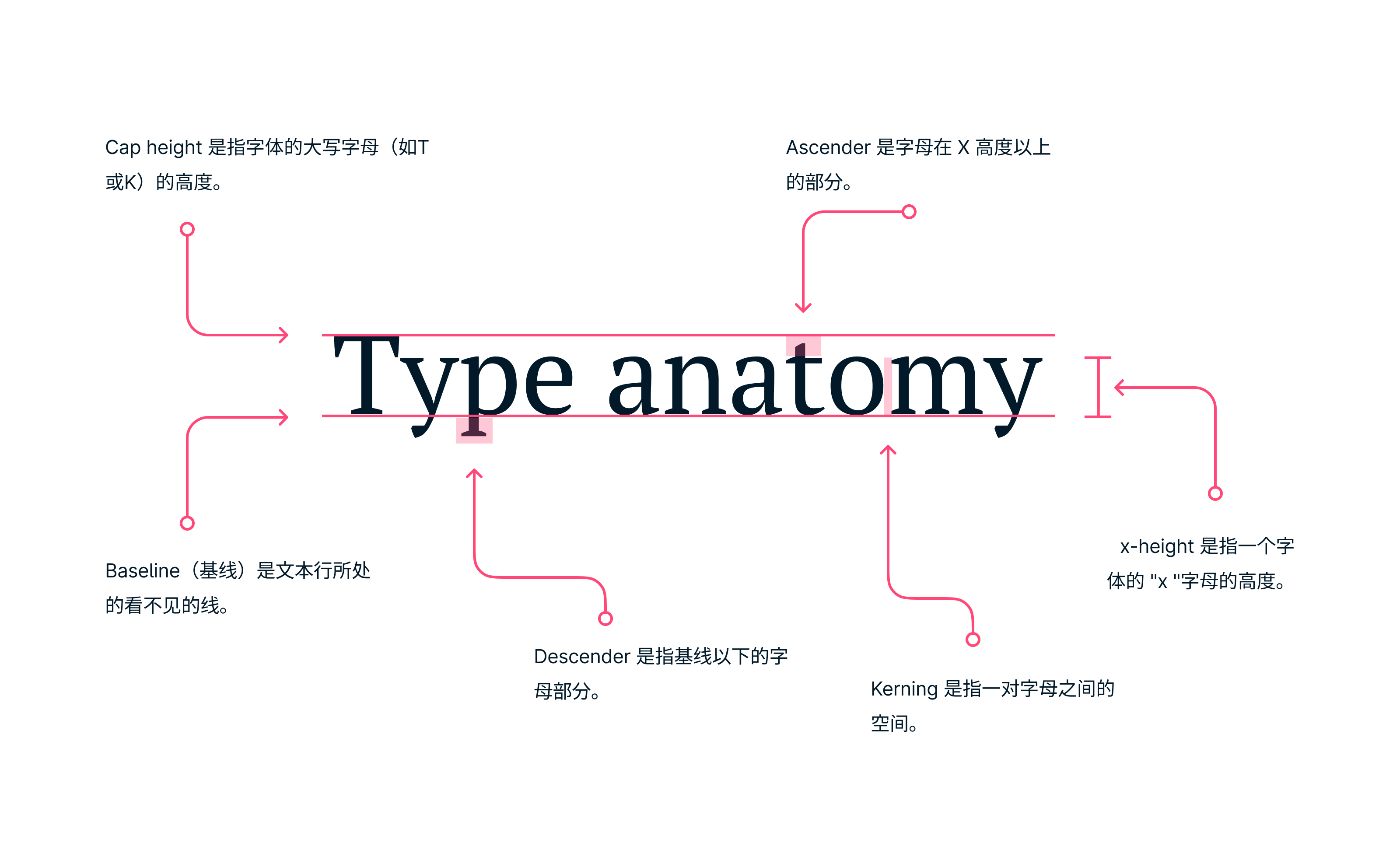
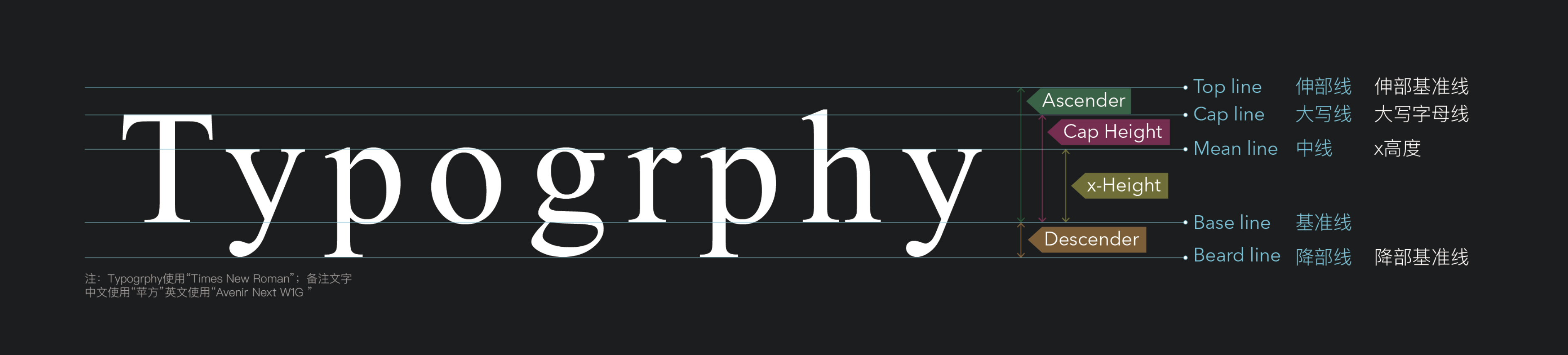
### 西文衬线体 Serif
#### Old Style 老式衬线体
老式衬线字体类似于用墨水书写。它们的特点是笔画粗细对比度低,笔画中存在对角线压力(见红线)。它们被认为是最传统的衬线风格。
老式衬线字体代表着历史和遗产。顾名思义,它们很古老。这就是说,它们中的许多--例如 Garamond--被认为是永恒的。如果你为一个具有悠久历史和传统的公司做设计,它们将是一个完美的选择,但对于专注于创新、进步和当前时代的公司来说,就不是一个好的选择了。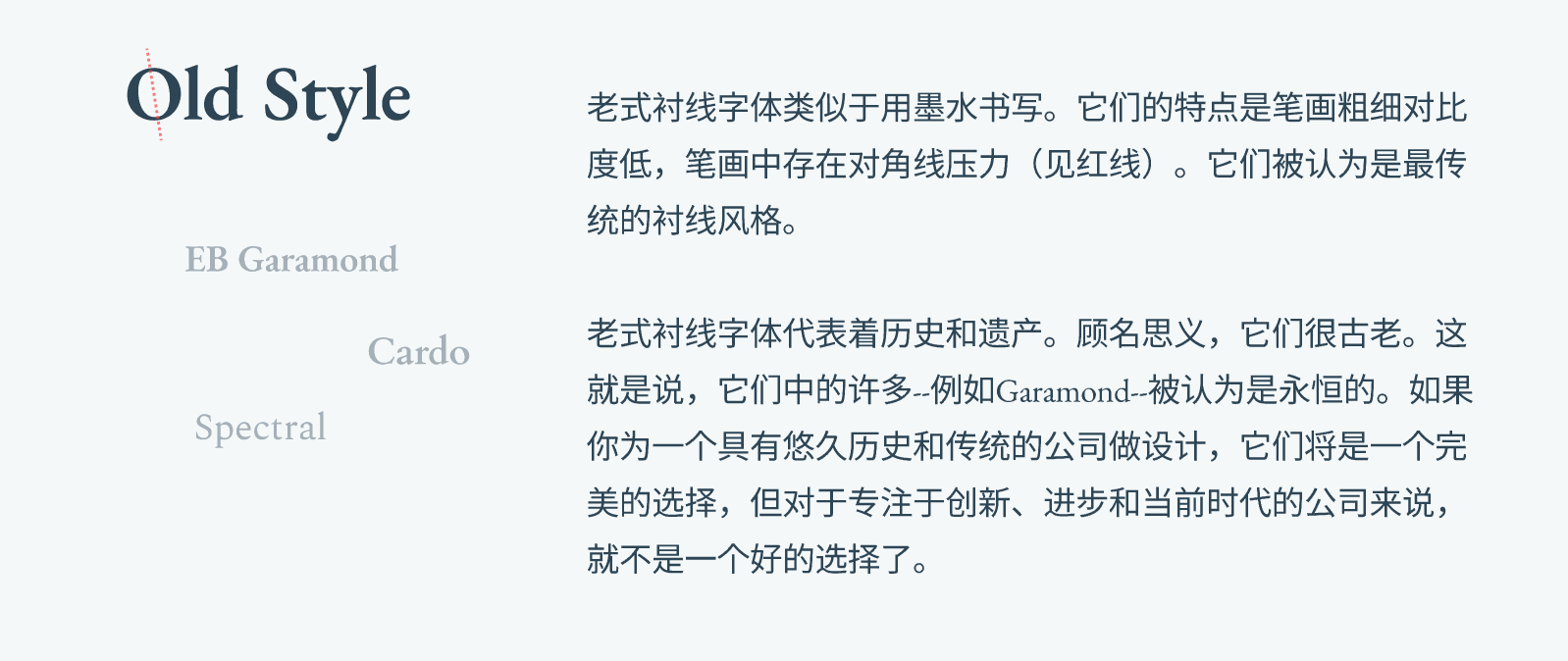
#### Transitional 过渡衬线体
过渡风格的特点是笔画的粗细对比度较高,笔画中的垂直压力较大(见红线)。与旧式风格不同的是,衬线也是有括号的。
过渡性衬线字体是非常通用的。它们是旧式风格和现代衬线之间的中间地带。这一类别的字体对于长篇文字来说是非常好的,例如用于**文章、博客文章甚至是书籍**。它们也代表着**安全、信任和传统**。
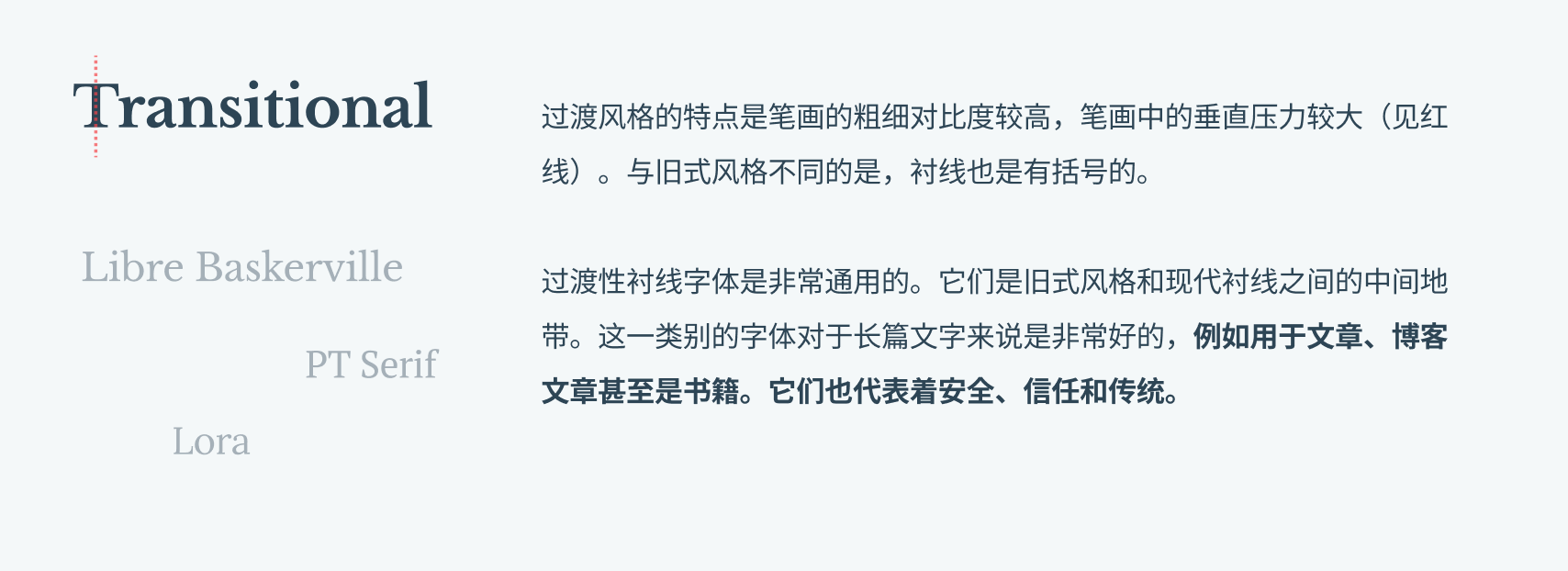
#### Neoclassical 新古典衬线字体
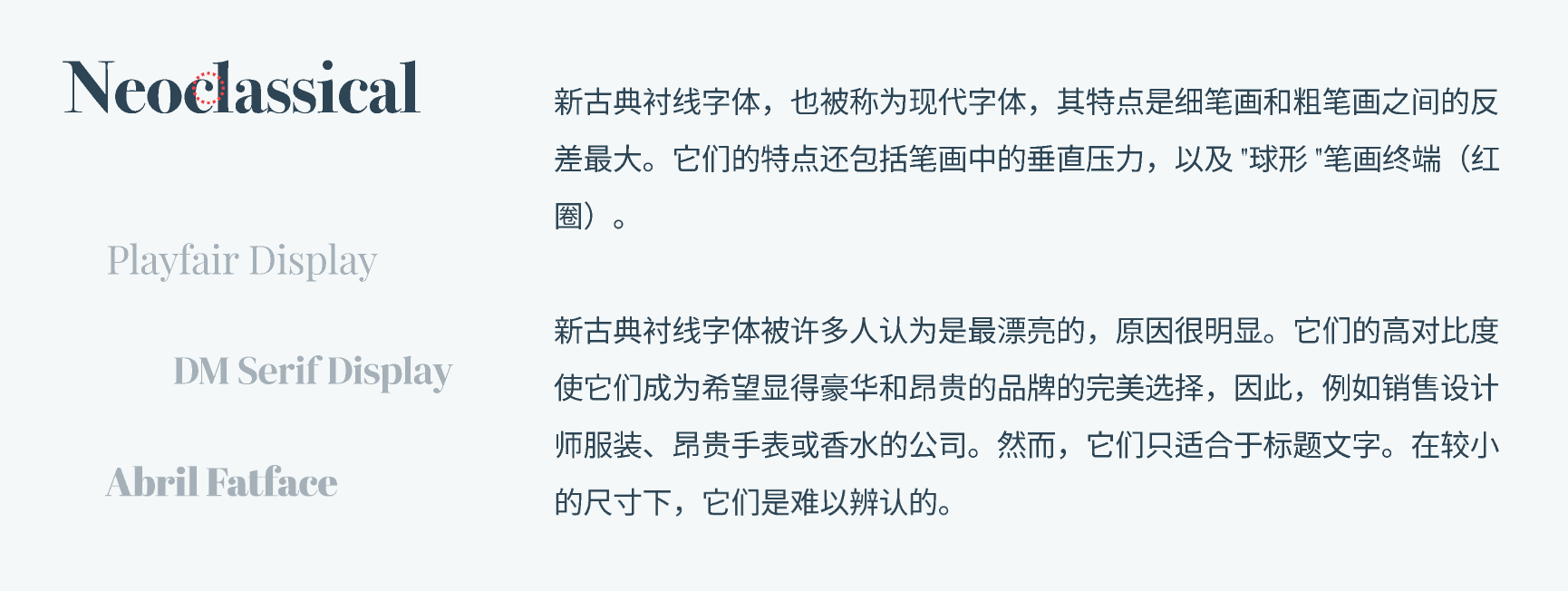新古典衬线字体,也被称为现代字体,其特点是细笔画和粗笔画之间的反差最大。它们的特点**还包括笔画中的垂直压力,以及 "球形 "笔画终端(红圈)。**
新古典衬线字体被许多人认为是**最漂亮**的,原因很明显。它们的高对比度使它们成为希望显得豪华和昂贵的品牌的完美选择,因此,例如**销售设计师服装、昂贵手表或香水**的公司。然而,它们**只适合于标题文字。在较小的尺寸下,它们是难以辨认的。**
#### Slab Serif 板式衬线体
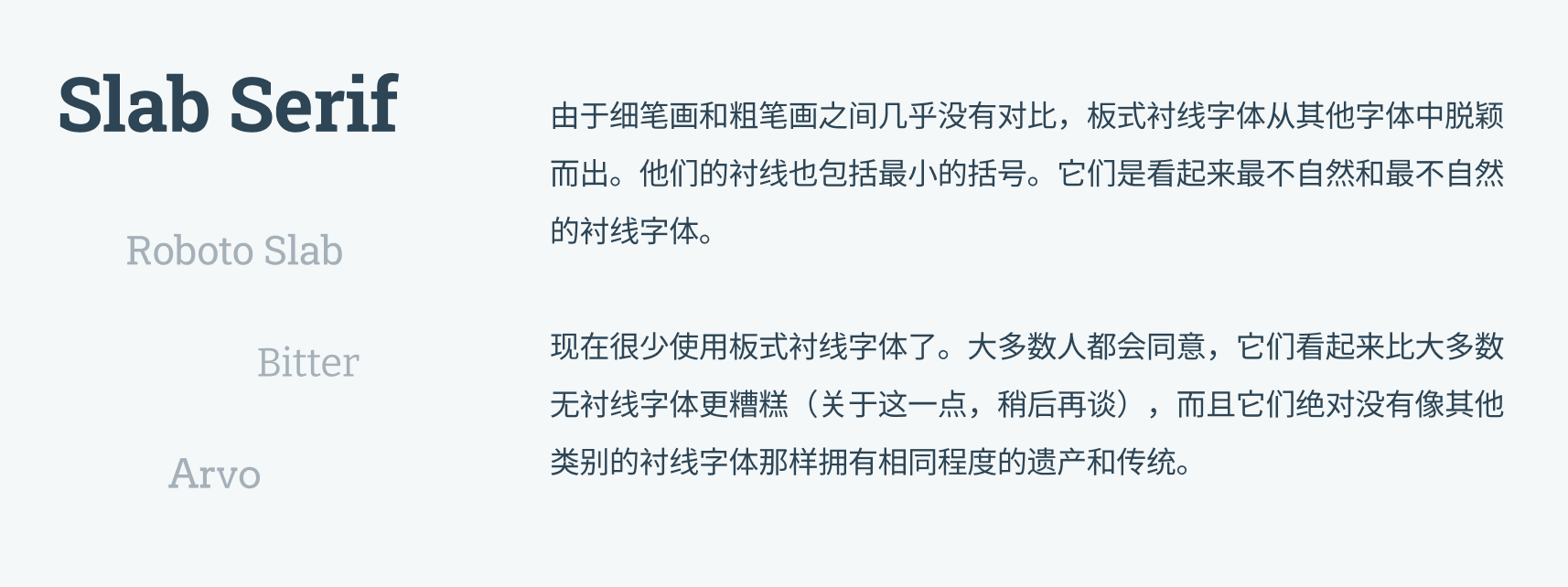
### Sans Serif 无衬线
#### Grotesque 怪异
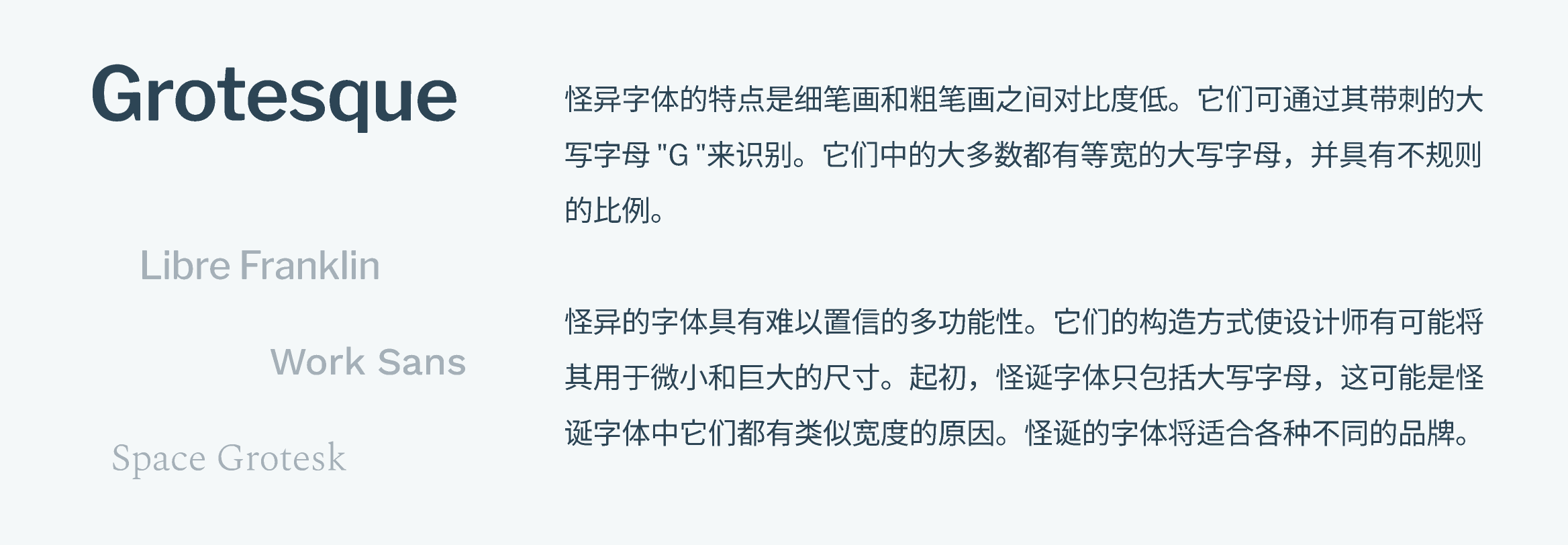
#### Humanist 人文主义
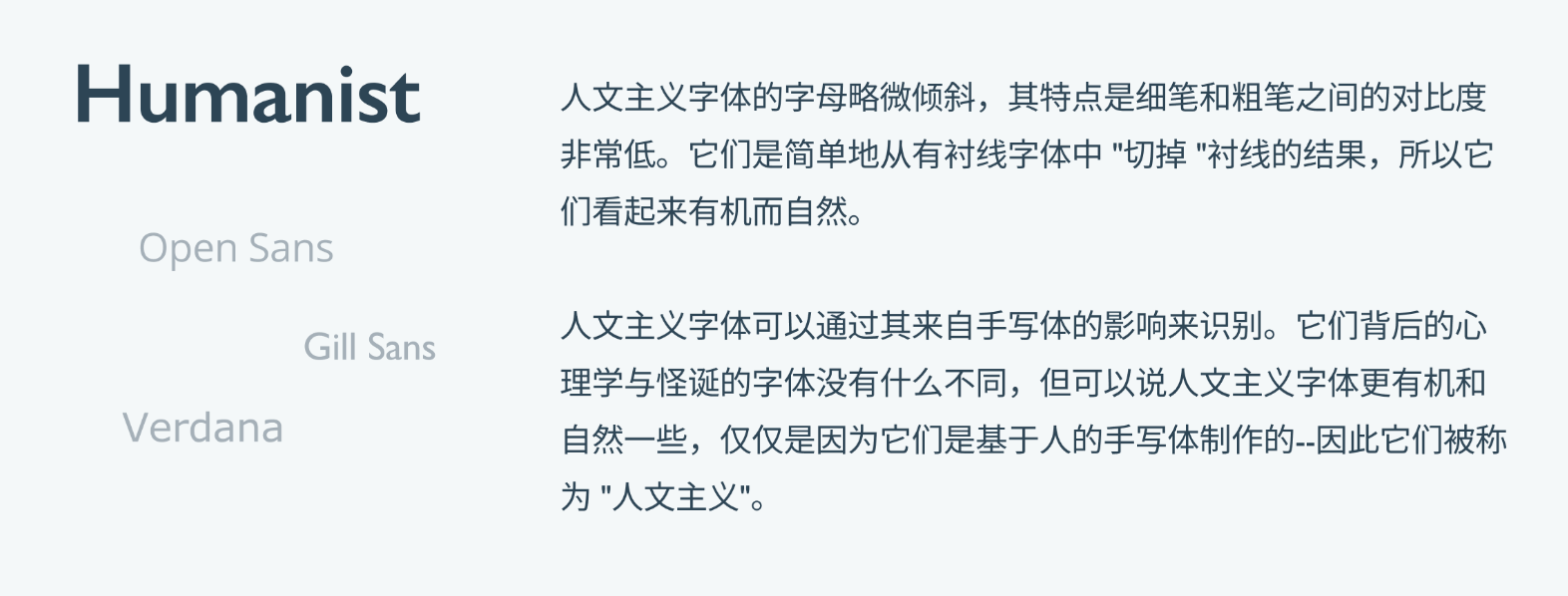
#### Geometric 几何
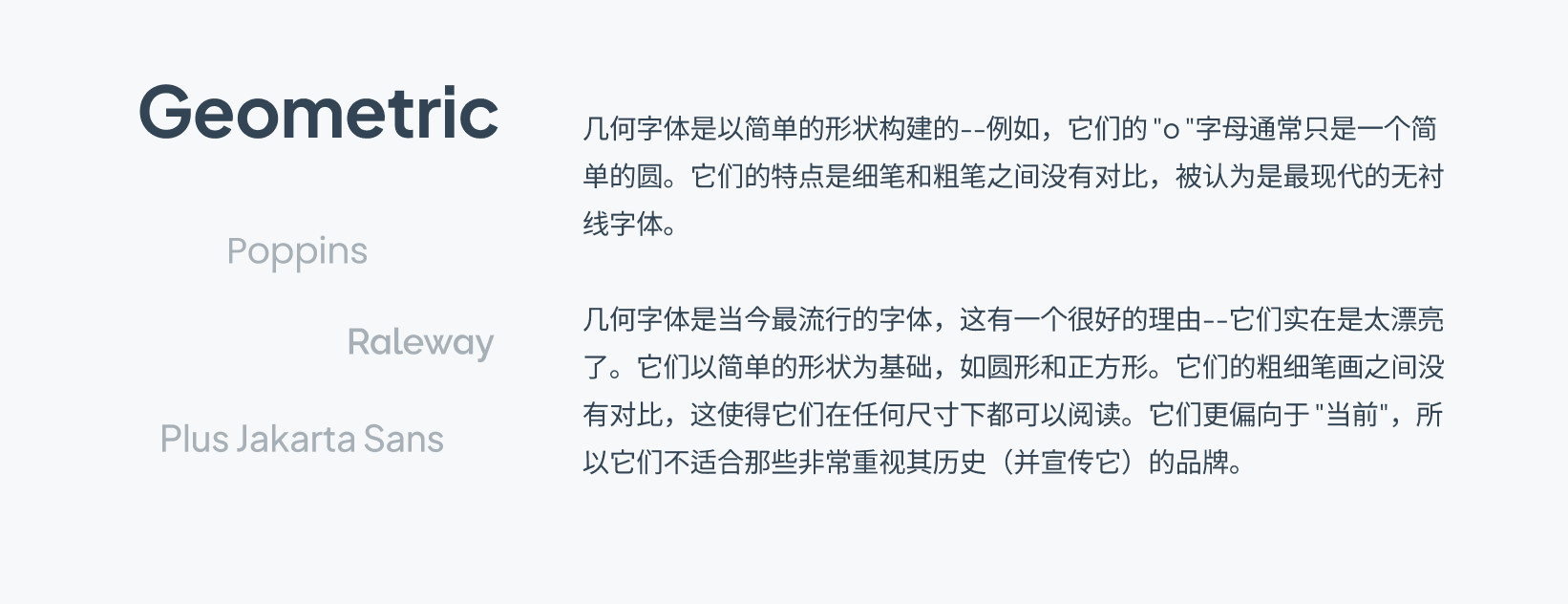
### Other style
#### Monospace
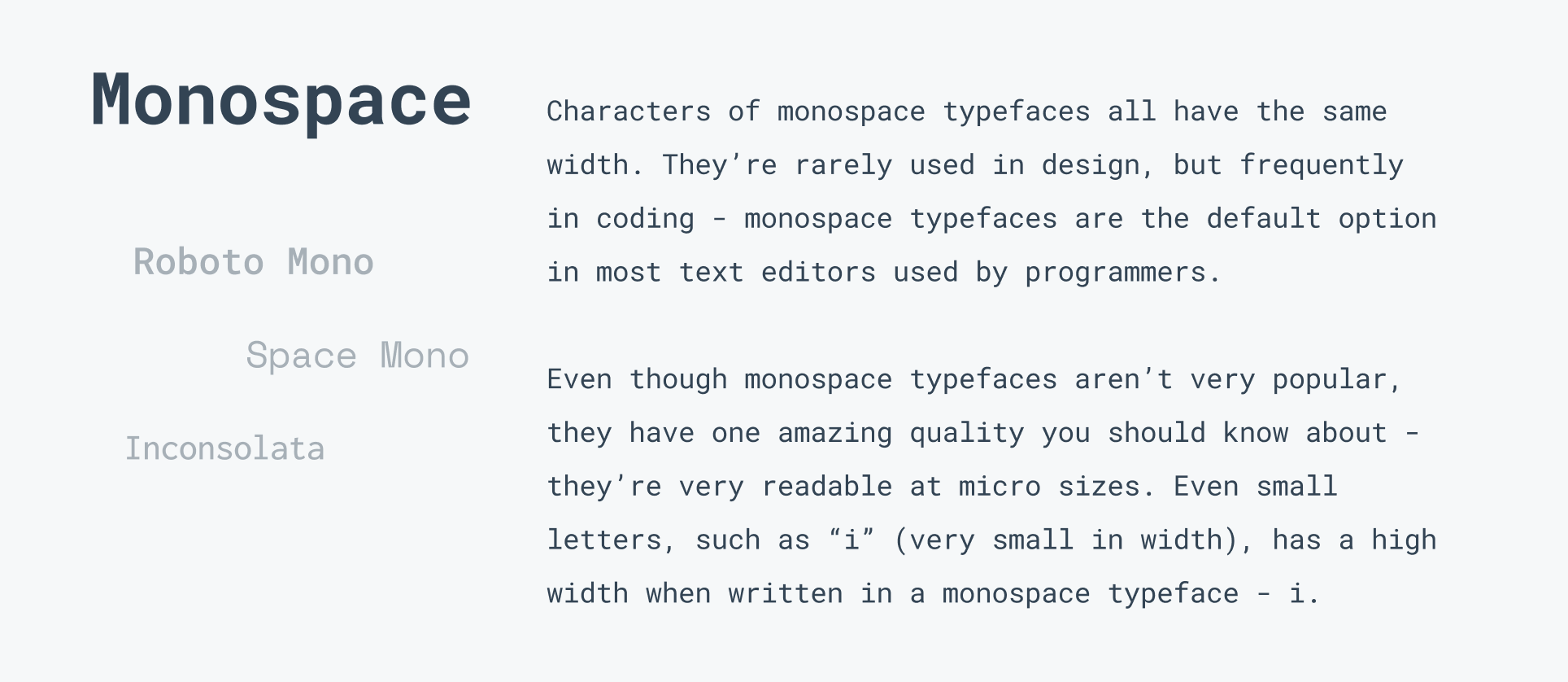
#### Handwriting
#### Display
## 识别字体
## 了解字体
### 预览效果
### 中文
### 英文
## 字体选择
### 常用英文字体
- [[Proxima Nova]] 之前看人人竞品时经常看到
- [[Helvetica Neue]] 品质还不错,但字符间距太紧凑、且用 CSS 没办法调整成好看的效果,而且也并非跨平台可用的字型(用户需要专门安装,比较麻烦)。
- [[Poppins]],也是很常见,个人蛮喜欢的,就是数字不等宽。
- [[San Francisco]] 授权问题不可用。
### 常用五种英文字体(一个国外大佬的)
- [[Gilroy]]
- [[Robot]] #等宽字体
### 常用数字字体
- **等宽数字**
- Inter
- Sf pro display
- Din
- **网友讨论**
- Gaodel:设计很圆润,年轻化,可爱,非常适合一些偏年轻化的产品,同时字重非常适合金融产品的字重效果。
- Montserrat:很优雅的一个字体,用在数字上或者界面中非常的优雅。
- Poppins:比较现代的一个字体设计, #非等宽字体
- 看着很稳重,但由于不是等宽数字,用起来别扭。
- Bitter:字体和英文字体都很好用,是谷歌旗下的一款产品,
- Graduate:非常英伦风格和学院风的一款数字字体,用于海报或者一些个人化活动页面效果非常好。
- Futura:这个无论是英文还是数字都非常现代化,非常干净利索的一款字体,做到 ppt 里效果非常好。
- Proxima nova:是一款收费字体,非常的优雅以及现代。
- Gotham:非常适合发布会,极简的网站设计,或者海报,非常现代干净的一款字体 #收费
- **Lato:** 非常现代科技感的一款字体:出自谷歌旗下。 #等宽字体
- 预览
- 有 figma 群友推荐 2021.12.12
- 衬线: playfair dispaly: 古典,现代,优雅与一体的一款设计。
- Oswald 不要钱;马丁老师推荐 #非等宽字体
- [[Din]] 很贵
- Fialla one:算是 din 的一款替代产品。
- [[inter]] 开源
![[Pasted image 20210326132942.png]] 来自 figma 模板站管理后台组件页面
### 可爱英文字体
- Nunito #Free开源免费 ![[Pasted image 20210525094250.png]]